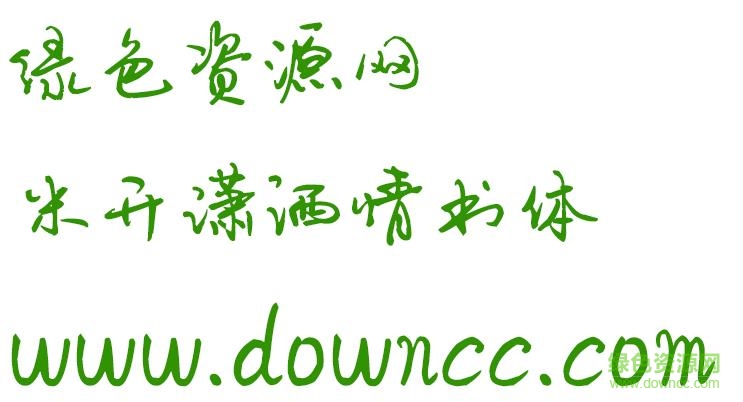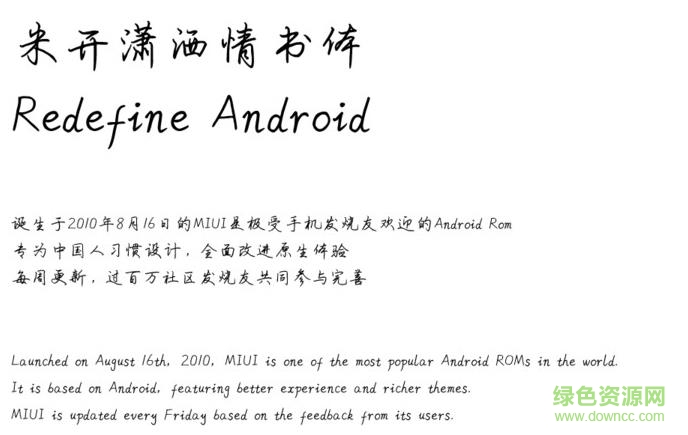
米開(kāi)瀟灑情書(shū)體ttf資源提供大家免費(fèi)下載使用,讓你在電腦上能夠感受到這款字體的獨(dú)特效果,擁有如情書(shū)一般的濃厚色彩,寄托了許多纏綿悱惻的字體風(fēng)格十分有趣!
米開(kāi)瀟灑情書(shū)體是一款硬筆書(shū)寫(xiě)行書(shū)字體,瀟灑漂亮,流暢自然,書(shū)生氣濃重,效果非常好,還需要其他自己可以在綠色資源網(wǎng)檢索下載哦!